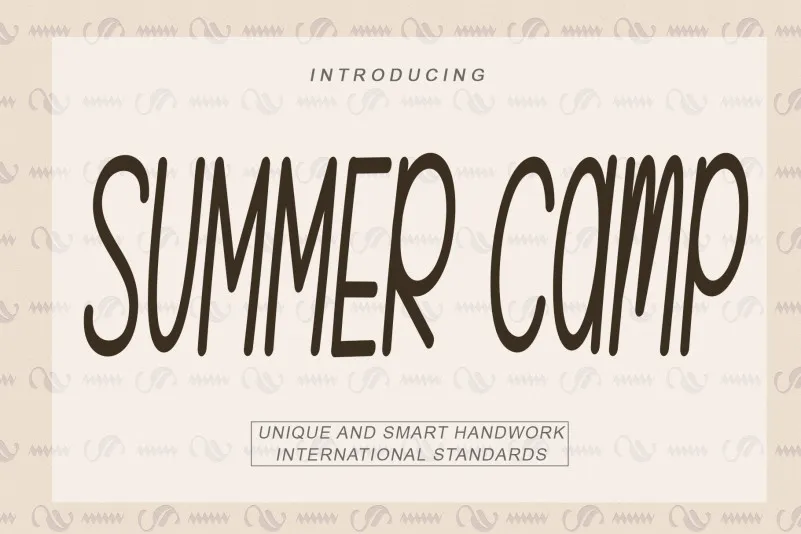
A nova Summer Camp Font é uma escolha perfeita para aqueles que buscam adicionar um toque familiar a seus projetos digitais. Desenvolvida pela talentosa designer kateengciu, essa fonte é uma cópia fiel de letras escritas à mão, simples e amigável. Permanece limpa e elegante, tornando-se um recurso valioso para qualquer biblioteca de fontes. Suave e acessível em qualquer aplicação, seja ela um projeto de design gráfico ou o layout de uma página web, essa fonte possui a habilidade inegável de revolucionar suas criações. Seja você um designer de sites profissional, criando páginas elegantes com apenas alguns cliques, ou simplesmente alguém que quer dar um toque pessoal à sua próxima obra de arte digital, Summer Camp Font é definitivamente uma fonte a ser considerada.